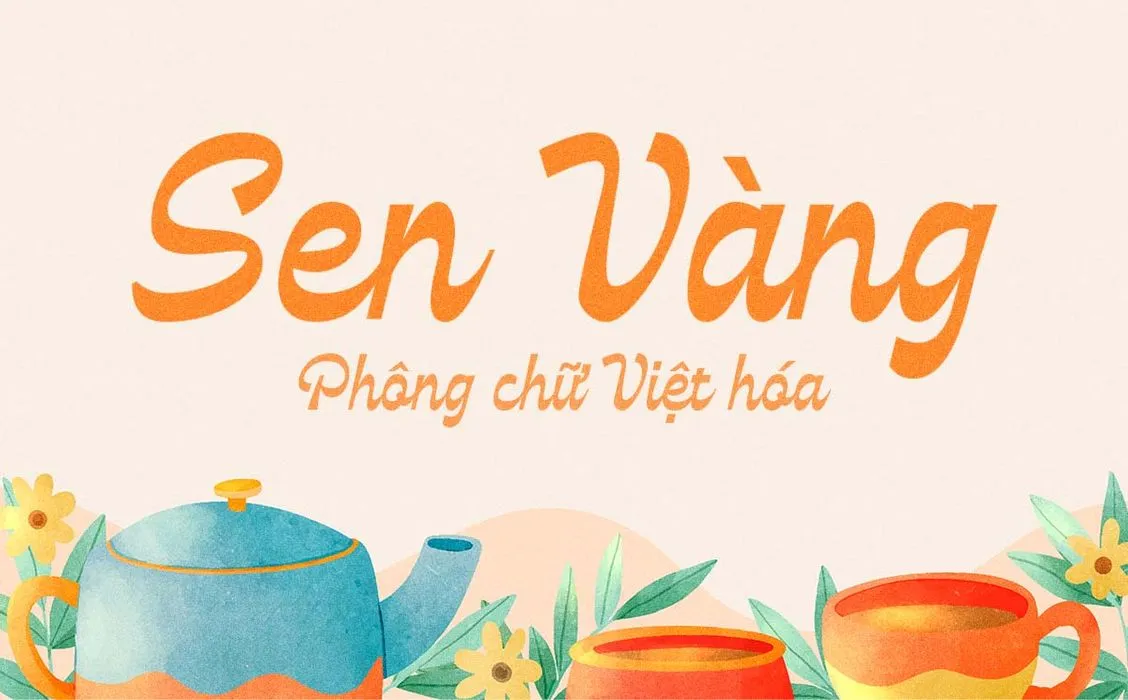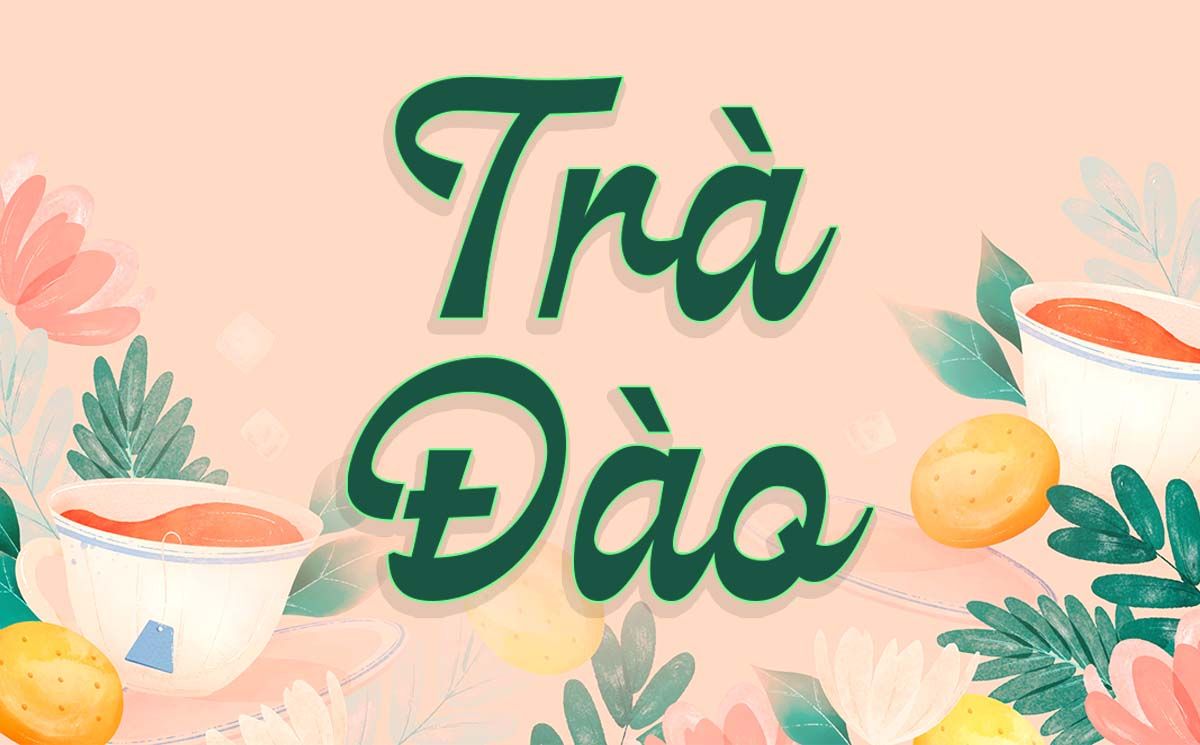
Font chữ TH Beltra là phiên bản Việt hóa của font Beltra nổi tiếng, được Việt hóa tỉ mỉ bởi Phạm Sơn – Admin
Với sự điều chỉnh chuẩn xác từng ký tự có dấu tiếng Việt, TH Beltra mang đến trải nghiệm trọn vẹn cho người dùng trong nước, giúp bạn thoải mái sáng tạo mà không lo bị lỗi font hay thiếu ký tự.
TH Beltra thuộc nhóm font chữ viết tay (script font), mang phong cách trẻ trung, mềm mại và giàu cảm xúc. Nét chữ tròn trịa, uốn lượn tự nhiên kết hợp với sự dày dặn, chắc chắn trong đường nét giúp font vừa mang vẻ thanh lịch vừa toát lên sự mạnh mẽ, hiện đại. Chính vì vậy, TH Beltra rất phù hợp trong nhiều lĩnh vực thiết kế như:
Logo thương hiệu: tạo sự khác biệt, cá tính và chuyên nghiệp.
Poster, banner, typography: thu hút ánh nhìn ngay từ cái nhìn đầu tiên.
Bao bì sản phẩm, nhãn mác thời trang, mỹ phẩm: truyền tải tinh thần sang trọng và sáng tạo.
Ấn phẩm cá nhân: thiệp mời, bìa sách, bìa tạp chí hoặc thiết kế social media.
Điểm đặc biệt của TH Beltra nằm ở sự liên kết mượt mà giữa các ký tự, nhờ đó chữ viết luôn liền mạch và sống động. Ngoài ra, font còn hỗ trợ đầy đủ tiếng Việt có dấu cùng nhiều ngôn ngữ khác, đảm bảo linh hoạt cho mọi dự án.
Nếu bạn đang tìm kiếm một font chữ viết tay Việt hóa vừa đẹp, vừa độc đáo lại chuẩn SEO, TH Beltra chắc chắn là lựa chọn không thể bỏ qua. Với sự chăm chút kỹ lưỡng từ Phạm Sơn, font mang lại chất lượng cao, thích hợp cho cả thiết kế cá nhân lẫn dự án thương mại.